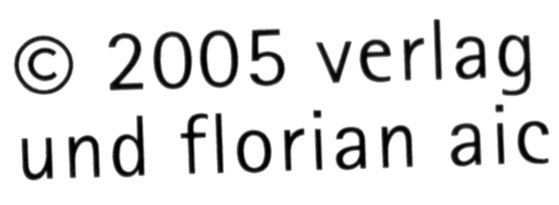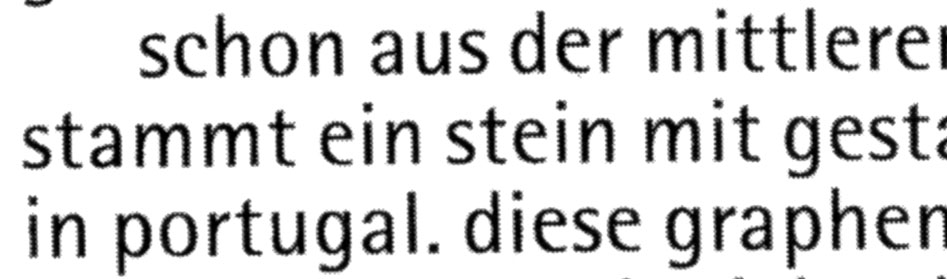
Zur Typographie im Reprint von Aichers "typographie&amp
Hab gestern freudig in der FH einen 2005-Reprint des bekannten Typowerkes entdeckt, abgeschleppt und reingestöbert, nun bis ich - gelinde gesagt - zutiefst irritiert:
Die Typo im Fließtest ist rotis semi sans, optisch halbfett, ohne Versalien; ihr werdet das ja wissen (habt´s wohl alle im Regal), ist eh alles andere als lesefreundlich in seiner leicht gesperrt wirkenden Anmutung.
Nun entdecke ich, auf verschiedenen Seiten unterschiedlich ausgeprägt, jedoch auch richtig rauhe Buchstaben, sieht aus wie 300dpi-Laser von 1995. Auf manchen Seiten geht das soweit, als wär die Schrift leicht weichgezeichnet und die (Graustufen-)Ränder dann von einem Laser aufgerastert. Richtig leseunfreundlich.
Meine Frage:
Der 2005er Reprint ist "eine fortomechanische Originalreproduktion der 2. Auflage 1989". War dort der Druck auch schon so rauh?? Ne, oder? Ist das also bei der Reproduktion so entstanden? Wenn ja: geht denn sowas nicht besser? Ich mein, da redet Aicher 250 Seiten lang von optimaler Lesbarkeit und ich muss mich Seite um Seite abkämpfen mit a. halbfetten rotis-Minuskeln und b. technisch unzureichender Wiedergabe.
Bin gespannt, wär natürlich toll, wenn jemand beide Ausgaben schon verglichen hätte.
Ich habe die Neuauflage nur im Buchladen durchgeblättert – mein flüchtiger Eindruck war auch: Ja, die Erstausgabe war prägnanter und schärfer gedruckt. Nachgeprüft habe ichs aber auch nicht – mir macht die Schrift ohnehin Kopfschmerzen.
Vielleicht erzeugt das Rotis-Bashing von HPW ja tatsächlich eine Art von Placebo-Effekt… Im Ernst: Bei längeren Texten habe ich sehr Mühe mit der Schrift.
Mir liegt es fern, diese Type zu verteidigen, aber daß das Geschimpfe inzwischen zum guten Typografen-Ton gehört, nervt dann doch „ein wenig“.
Fühle Dich bitte nicht angesprochen, Deine Theorie klingt auch recht einleuchtend. Ich denke da eher an Leute, die die Rotis gerade erst von der Arial zu unterscheiden gelernt haben, aber schon wie die Großen schimpfen.
Nur so schnell angedacht: Wenn Schriftgestalter eine Schrift nicht nur als Kommunikationsmedium, sondern als Teil eines größeren ästhetischen – oder gar lebensphilosophischen – Projekts sehen, wie das bei der Rotis der Fall ist, besteht die Gefahr, dass die theoretischen Konzeptionen der Praxistauglichkeit davonlaufen. Mit anderen Worten: Die Beschreibung Aichers leuchtet mir größtenteils ein, in der Praxis hält die Schrift jedoch längst nicht das, was sie theoriegemäß sollte.
Ähnlich ging es mir bei einigen Schriften – besser: Schrift-Einsätzen – der ‹Schweizer Schule› (Emil Ruder u. a.). Auch dort ist Schrift nur Teil eines größeren ästhetischen Projekts, funktioniert aber bei längeren Texten nicht so gut, wie es die Theorie behauptet.
Bei Frutiger hingegen ‹stimmt› meist Theorie und Praxis überein – trotz seiner je länger, je anthroposophisch-esoterischeren Kontextualisierungen…
Nun, mein Ansinnen wars auch gar nicht, wieder eine Rotis-Diskussion zu entfachen. Ich persönlich find sie genial für Headlines und problematisch in Lesetexten, aber das tut nichts zur Sache. Was mich erstaunt, ist einfach die unbefriedigende technische Reproduktion dieses Buches. Und ich hätt gern abgeschätzt, worauf das zurückzuführen ist: bereits auf die Erstausgabe, die ich nie in der Hand hatte oder erst auf die Repro. In einem (so teuren) Buch mit 1A-Papier vom (wunderbaren) Schmidt-Verlag hätt ich das nicht erwartet, ich wär bei Kauf arg enttäuscht: bei solchen Büchern zahl ich persönlich nicht nur für Sachinformation, sondern auch für einen typographischen Augenschmaus. Wie lang war ich an der "Lesetypographie" von HPW gesessen: nicht, dass ich in den nächsten 5 Jahren ein Buch zu setzen gedenke, aber es ist nicht nur informativ, sondern auch schön und schult das Auge.
Was mich erstaunt, ist einfach die unbefriedigende technische Reproduktion dieses Buches. Und ich hätt gern abgeschätzt, worauf das zurückzuführen ist: bereits auf die Erstausgabe, die ich nie in der Hand hatte oder erst auf die Repro.
Die Originalauflage aus unserer Bibliothek ist technisch einwandfrei.
In einem (so teuren) Buch mit 1A-Papier vom (wunderbaren) Schmidt-Verlag hätt ich das nicht erwartet, ich wär bei Kauf arg enttäuscht: bei solchen Büchern zahl ich persönlich nicht nur für Sachinformation, sondern auch für einen typographischen Augenschmaus.
Ich habe den Reprint leider noch nicht gesehen, denke mir aber wenn es besser ginge hätte der Verlag das gemacht (so wie ich Schmidt kenne).
Schade ist es trotzdem, ich werde mir das Buch wohl in der Buchhandlung erst ansehen müssen bevor ich es kaufe.
einfach nur nochmal als Veranschaulichung:
das ist ein 6oodpi-Scan aus dem neu gesetzten Impressum:
aicher_neusatz.jpg
Das dagegen ist (mit identischen Scan- und Speicherparametern) aus dem reproduzierten Teil:
aicher_repro.jpg
Das wirkt mit bloßem Auge nicht sooo dramatisch, aber eben schlecht gedruckt.
Oder ihr macht 50/50, er zahlt 11, du legst 11 dazu und hast nachher die Schrift, vielleicht brauchst du sie ja nochmal.